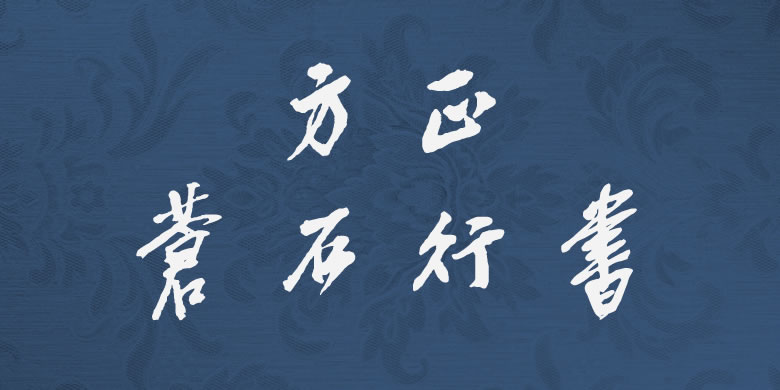
方正苍石行书
吴昌硕(1844—1927)初名俊,又名俊卿,字昌硕,又署仓石、苍石,多别号,常见者有仓硕、老苍、老缶、苦铁、大聋、缶道人、石尊者等。晚清民国时期著名国画家、书法家、篆刻家,“后海派”代表,杭州西泠印社首任社长,与任伯年、蒲华、虚谷合称为“清末海派四大家”。篆刻家,与任伯年、赵之谦、虚谷齐名为“清末海派四大家”。其书法用笔多以中锋篆隶笔法,富有金石气息,结体开张爽健,有雄强老辣的艺术感染力。吴昌硕留下了大量书作,画作也多有长款,搜集遴选并调整补充,做成了这款字库。